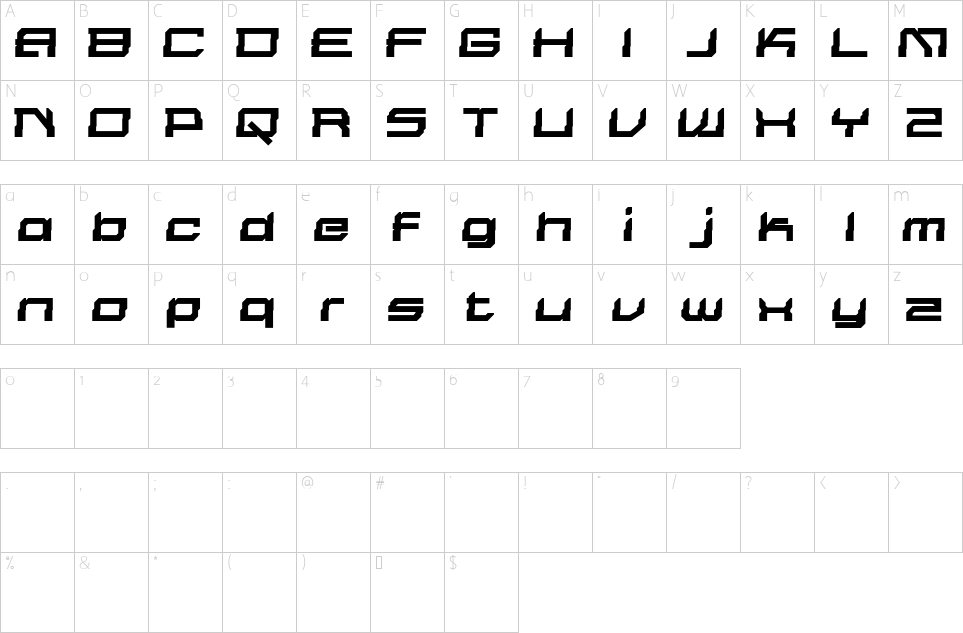
Guinsa Font
A Guinsa Font é uma elegante e versátil escolha para qualquer designer que busca uma tipografia com ares descontraídos e atuais. Desenhada por Craft Supply Co, esta fonte oferece um estilo fresco que combina elementos modernos com sutis toques vintage. Com seu design cuidadosamente elaborado, a Guinsa é perfeita para uso em materiais digitais ou impressos, proporcionando uma aparência sofisticada e única ao seu projeto. Esta fonte já foi baixada 84 vezes, o que demonstra sua popularidade entre designers e criadores de conteúdo. Se você busca adicionar um toque moderno à sua identidade visual sem sacrificar um pouco do clima aconchegante dos anos 90 ou 2000, a Guinsa pode ser exatamente a fonte que está procurando. Engane-se e desfrute de uma experiência criativa mais gratificante com essa fonte gratuita para Windows e Mac.